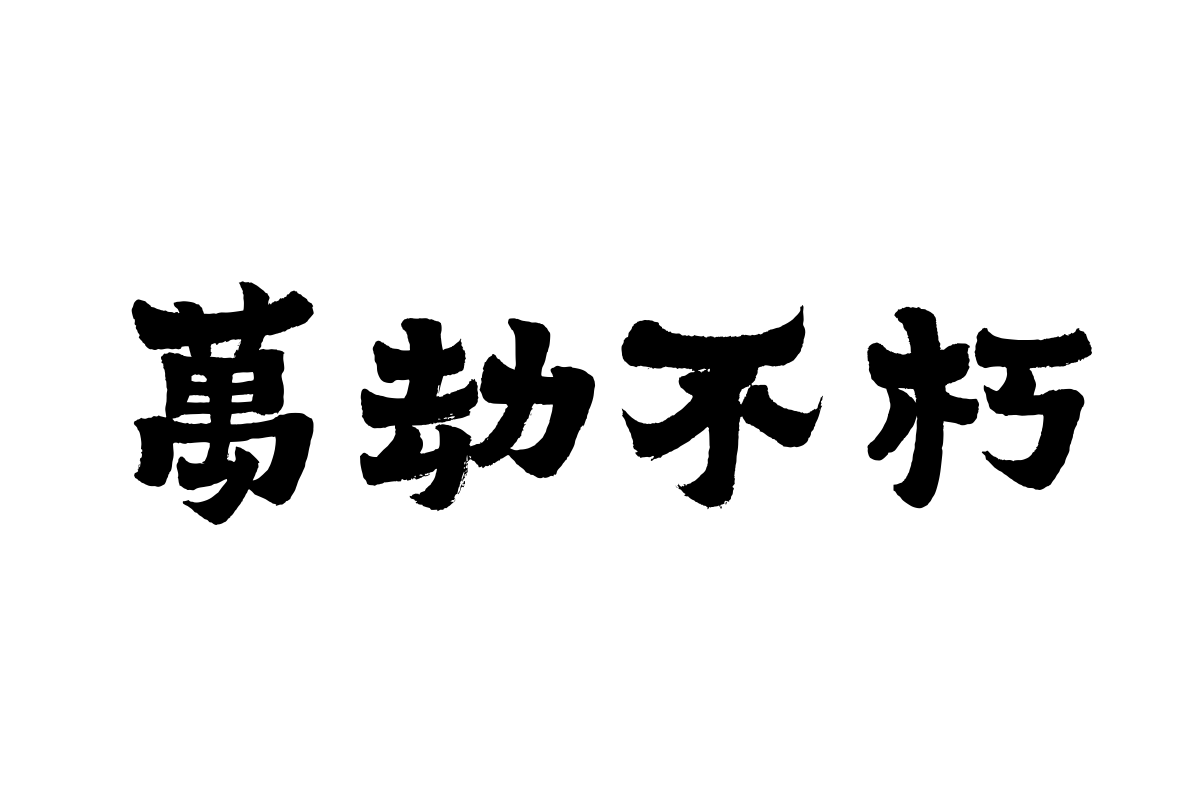
汉仪容慈厚隶繁是一款具有深厚历史底蕴和独特风格的字体。它源自古代的隶书,融合了现代审美观念,形成了一种既庄重又亲切的字体风格。
该字体的特点如下:
1. 结构严谨:汉仪容慈厚隶繁在字形结构上非常严谨,每个笔画都经过精心设计,使得整个字体看起来既有力度又不失柔美。
2. 线条流畅:该字体的线条流畅自然,没有过多的装饰性笔画,给人一种简洁明快的感觉。
3. 易于阅读:由于其结构简单明了,无论是在正式场合还是日常生活中,汉仪容慈厚隶繁都能让人轻松阅读,不会感到疲劳。
4. 适合多种应用场景:无论是用于印刷品、广告、网页设计还是其他需要文字的地方,汉仪容慈厚隶繁都能展现出其独特的魅力。
总之,汉仪容慈厚隶繁是一款非常优秀的字体,它不仅具有深厚的文化底蕴,而且能够很好地满足现代人的审美需求。